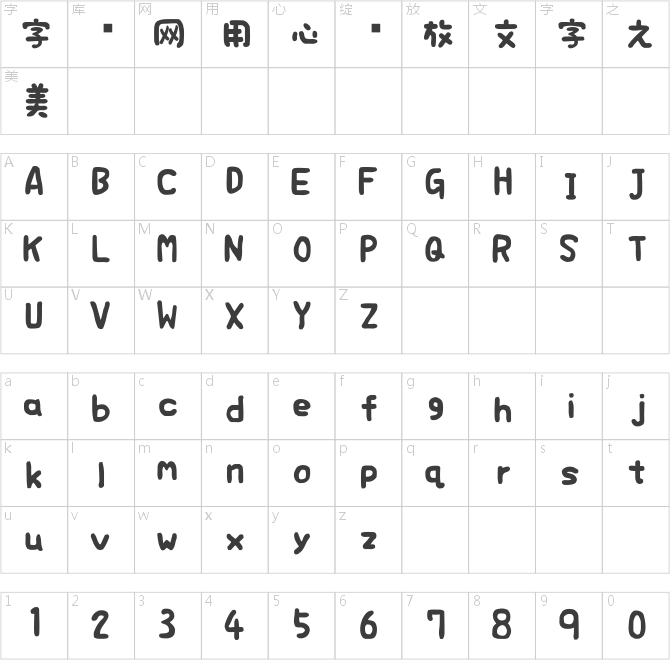
字體名稱: 豆豆字體Pえる
豆豆字體Pえるまー
えるまーフォント<等幅> ver.1.60
えるまーPフォント<プロポーショナル> ver1.60
マジックペンで書いたような手書きフォントです。<第二水準まで>
足跡やハート等が罫線の後半に入っています。「けいせん」を変換させてみてください。
豆豆字體Pえるまー字體Elmer_P Font字庫是一款讓人賞心悅目、百看不厭的日文字體,適合各類廣告和產品包裝設計應用,字體大小3.26MB,格式為ttf字體,上傳用戶是Apple,作者/版權方為隠れ家